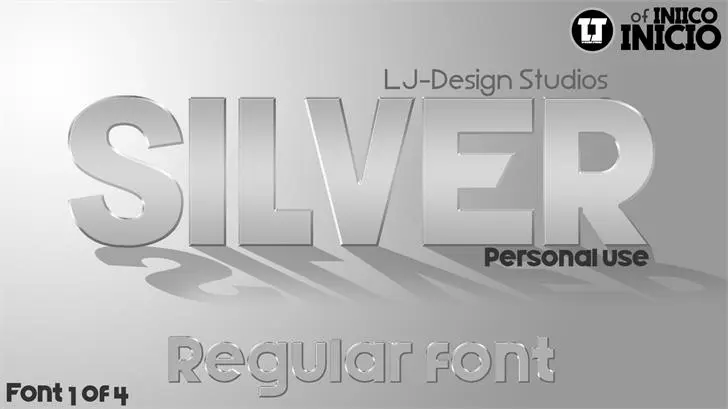
Silver Forte é uma fonte sans-serif criada em 2015 por LJ-Design Studios, adaptando sua famosa fonte Home para um formato mais personalizado e específico. Esta nova variação manufaturada atende a um público exigente que busca estilos menos convencionais em sua criação visual. O design de Hamilton dá ao Silver Forte uma cara fresca e moderna, ideal para trabalhos digitais como logos, banners, e materiais online. Seja você designer ou criador digital, este é o tipo certo para destacar seu trabalho pessoal sem perder a essência da sua personalidade. Compatível tanto com projetos pessoais quanto comerciais, Silver Forte oferece um conjunto de opções variadas, mantendo sempre uma estética forte e moderna. Para informações sobre uso comercial, basta entrar em contato conosco para obter as instruções adequadas.